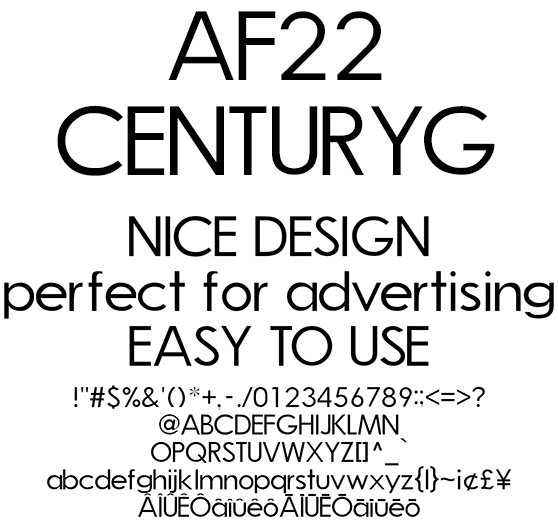
オールマイティな欧文 AF22CENTURYG
AF22CENTURYG
見慣れたデザインで読みやすいレギュラーウェイトのゴシック体、リーフレットやお洒落なドキュメントに最適。個人同人向けアニメ、動画向けなフォント。記号類、マクロンやサーカムフレックスなどのダイアクリティカルマーク追加。日本のローマ字表記で使われる訓令式やヘボン式で扱う Ô や Ō を収録、人名地名でもお使い頂けます。